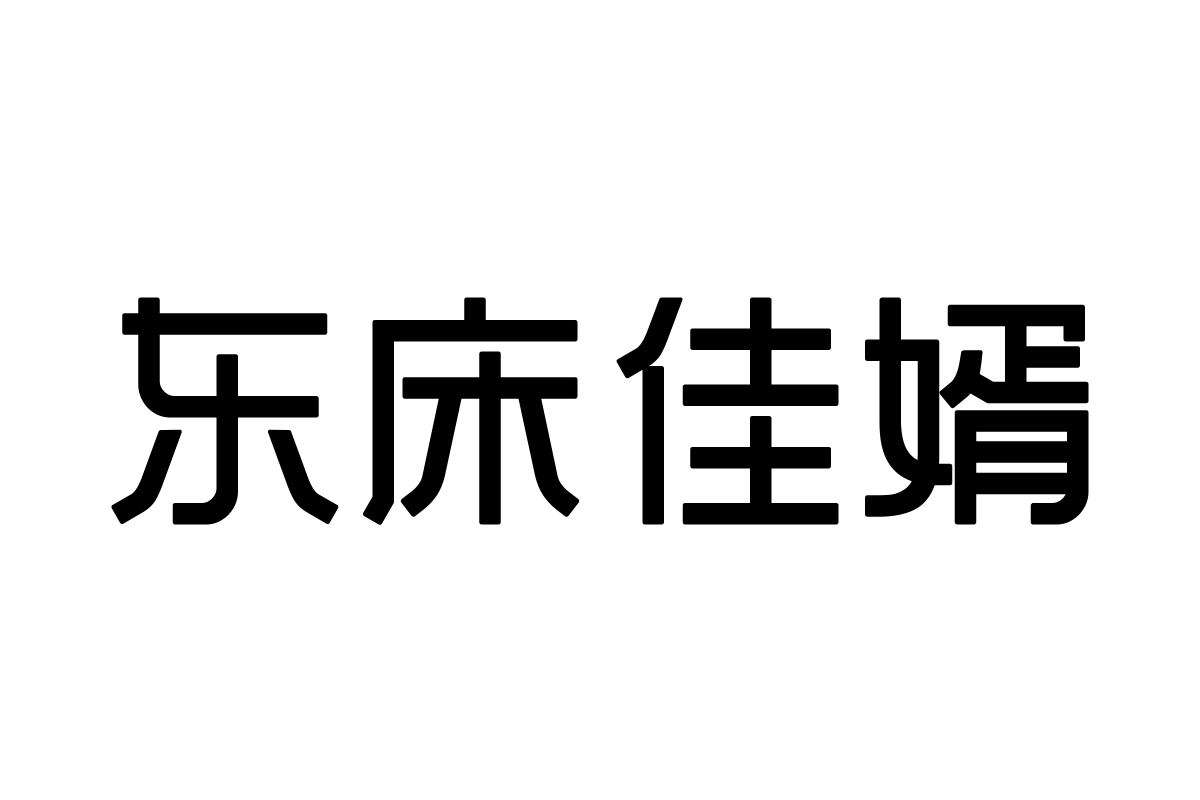
三极新客体字体是一款由上海三极信息技术有限公司设计开发的中文字体。它以其独特的风格和现代感而受到广泛欢迎。
三极新客体字体采用了简洁、流畅的线条和形状,使得文字在视觉上更加清晰易读。它的笔画粗细适中,既保留了传统汉字的特点,又融入了现代设计元素,使得整体效果更加时尚。
此外,三极新客体字体还具有一定的艺术性,通过巧妙的组合和排列,形成了独特的视觉效果。这使得它在印刷品、广告、网站等场合都能发挥出良好的视觉效果。
总之,三极新客体字体是一款集实用性和美观性于一体的优秀字体,适合用于各种需要展示文字信息的场合。